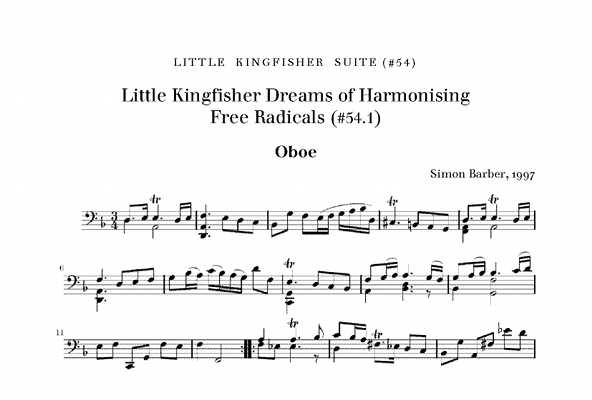
Bitte um Beispiele vorbildlich gesetzter Notenblätter
Vorab: Ich bin kein Typo-Experte.
Zur Zeit helfe ich einem guten Freund, einem Komponisten, sein gesamtes Werk zu überarbeiten.
Er kennt sich mit der Bedienweise von Software nur wenig aus. Insbesondere der Einsatz von Vorlagen war ihm bisher fremd.
Konsistenz in der Gestaltung/ im Erscheinungsbild gibt es daher bisher nicht. Schönheit/Eleganz auch nicht.
Es kann also nur besser werden.
Betrachten möchte ich im Moment nicht die Noten selbst, sondern nur die "Metabereiche" wie Werksname, Werksteilname, Werksname-Nummer, Werksteil-Nummer, Komponist, Jahr, Stimmauszugs-Bezeichner, Lizenzhinweis, Seitenzahlbereichs-Bezeichner, Seitenzahlen, ...
Einfache Skizze, angefertigt in Openoffice Writer:
http://borumat.de/+screenshots/sc-082.png
Die grauen und roten Linien werden nicht gedruckt. Sie sind "Textbegrenzungen" in OOo. Ich habe sie zur Visualisierung der Inhaltsbereiche dringelassen.
Zur besseren Übersicht in der Entwurfsphase habe ich die Seiten auf 10cm Höhe gestaucht.
Als Brotschrift wünscht sich der Komponist "Times New Roman". Er ist aber sicher auch für andere Serifenschriften offen.
Würd' mich sehr freuen, wenn ihr mir Hinweise auf, aus Eurer Sicht vorbildliche gesetzte/strukturierte/gestaltete, Notenblätter geben könntet.
Ich suche Inspiration.
Insbesondere interessiert es mich, was ihr zu den dreizeiligen Kopfbereichen und zur Nennung von vier Seitenzahlen (2 Bereiche: Gesamtdokument und aktueller Abschnitt) denkt.
Ich freue mich über Anregungen zu Proportionen, Weißraum, Überschriften-Fonts, Kopfbereich-Fonts, Schriftgrößen, Seitenrändern, Ausrichtungen, ...
Der Platz für die eigentlichen Noten ist viel zu klein auf der Seite (wenn ich Deine Beispiele richtig verstehe). Warum verwendest Du so ein seltsames Seitenformat? Die einzelnen Elemente der Titelseite wirken „aufeinandergeklatscht“, sie stehen zu eng.
Kennst Du Lilypond? Das solltest Du für hübschen Notensatz verwenden.
@Joshua K.
Wie schon geschrieben: die echten Seiten sollen selbstverständlich nicht auf 10cm Höhe gestaucht werden. Sie besitzen die normale A4 Höhe.
Übrigends zeigt der Screenshot nicht die Titelseite, sondern einen Bereich mittendrin. Genauer: den Beginn des Stimmauszuges für das Instrument Oboe.
Da typischerweise Musiker sich nur "ihren" Stimmauszug ausdrucken, beginnt auch dieser Teil mit allen wesentlichen Informationen:
Werksname, Werksnummer, Komponist, Jahr, Lizenz, Instrument, Werksteilname, Werksteilnummer
Zu Lillypond: Ich selber bin kein Komponist/Musiker.
Aber aus Neugier: kennst Du Lillypond aus eigener Erfahrung?
Falls ja: beherrscht es ausgefeiltes Arbeiten mit Dokument-, Seiten-, Absatz- und Zeichenvorlagen, ähnlich wie eine mächtige Textverarbeitung?
Kannst Du mir öffentlich einsehbare Notenblätter zur Ansicht empfehlen, die mit Lillypond erstellt wurden?
Wie schon geschrieben: die echten Seiten sollen selbstverständlich nicht auf 10cm Höhe gestaucht werden. Sie besitzen die normale A4 Höhe.
Hoppla, das hab ich glatt überlesen! :oops:
Ich selbst habe Lilypond noch nicht benützt, habe aber einmal mit einem Musiker zusammengearbeitet, der es verwendet. Es gilt wohl als das Programm, das den besten Notensatz erzeugt (auch besseren als das LaTeX-Paket „MusiXTeX“).
Lilypond ist aber kein Textverarbeitungsprogramm, sondern setzt nur Noten. Es gibt aber auch ein Programm, das Lilypond in OpenOffice integriert: OOoLilyPond.
Ein Lilypond-Beispiel: baerenreiter-sarabande.pdf
Ich habe mal auf die Schnelle ein Beispiel für eine bessere Aufteilung Deines „Seitenkopfes“ zusammengefrickelt:
sd07ee.png
Ich würde an Deiner Stelle einfach mal in eine Musikbuchhandlung gehen, und ein paar Noten anschauen, und dabei auf die übliche Aufteilung von Titel, Komponist usw. achten. (Wenn möglich sieh Dir handgestochene Noten an, die haben die höchste Qualität.)
Ich habe mal auf die Schnelle ein Beispiel für eine bessere Aufteilung Deines „Seitenkopfes“ zusammengefrickelt
Ah, wohltuend. Gleich vielviel besser!
Deine Notenschrift gefällt mir gut.
Würde auch zu Liederbüchern passen.
@Joshua
Herzlichen Dank für das Erstellen des Beispiels. :)
1 Zentrierung
2 Versalien für Werksname (Überschrift der Ebene 1)
3 Werksteilname (Überschrift der Ebene 2) größer als Werksname
4 Instrumentenname hinter Ü2
5 Komponist und Jahr rechtsbündig
6 keine typographische Unterscheidung der Werksnummer, bzw. Werksteilnummer gegenüber der jeweiligen Überschrift
7 Änderung der Schreibweise: Versalien am Anfang von Wörtern
Zu 2:
Ich gestehe offen, dass meine Augen Versalien nicht besonders mögen.
Zu 4:
Die Reihenfolge der Inhalte ist:
* Stimmauszug Oboe für Werksteil 1
* Stimmauszug Oboe für Werksteil 2
* Stimmauszug Oboe für Werksteil 3
* Stimmauszug Violine für Werksteil 1
Über das enge (programmunabhängige) Thema des Threads hinaus, brennt mein Freund, der Komponist darauf, mehr zu den Eigenschaften/Vorzügen von Lillypond zu erfahren.